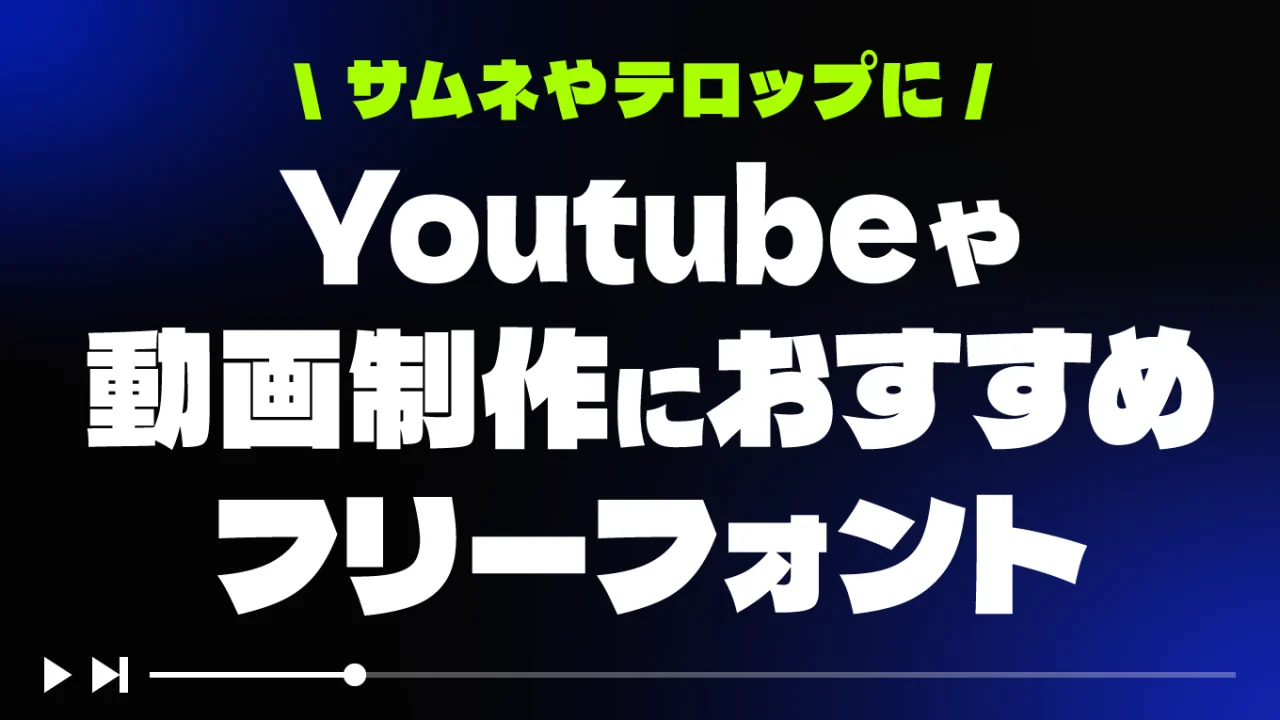
YouTube動画制作の字幕・タイトル・アイキャッチ画像やサムネイル画像におすすめフリーフォントをまとめています。
フォントが変わるだけでガラッと動画の印象が変わるので、自分の動画スタイルにあったフォントを選ぶことがポイントです。
さまざまなYoutube動画のアイキャッチやテロップ使用されているフォントや、Youtuberに人気のあるフォントや動画制作で定番フォントなどのおすすめフリーフォントをご紹介します。
動画制作の字幕やタイトルにフリーフォントのまとめ
本記事で紹介している一部のフォントですが、Youtubeのサムネイルやテロップに使用するとこのようなイメージになるので、フォント探している方は参考にしてみてください。
きんいろサンセリフ
きんいろサンセリフフォントは、人気4コマ漫画のタイトルロゴをモチーフに制作されたフォントです。ユニークなフォルムがポップな印象がでるので、VTuberさんの動画がよく使用されているのを見かけるフォントです。
ABEMA番組「チャンスの時間」番組内のテロップに使用されているので、TV映像でも使われる人気あるフォントです。
キルゴUフォントは、アニメロゴをモチーフとしたフォントです。ゴツゴツしたフォルムが元気でポップな印象なので、サムネイルに取り入れるとインパクトがでること間違いないフォントです。
源暎きわみゴ
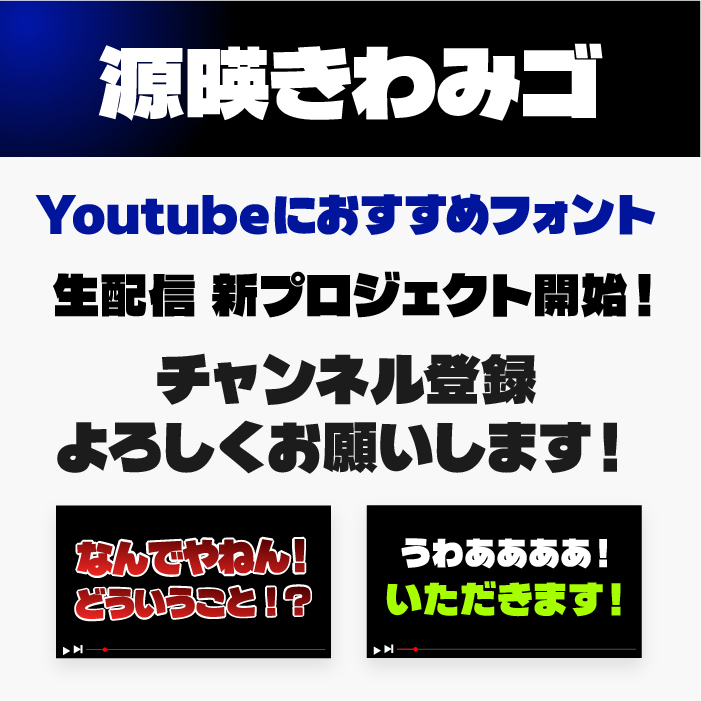
源暎きわみフォントは、超極太フォントで視認性・判読性も高く、強い印象があり、目を引くフォントなので、サムネイルやテロップなどにさまざまな場面で活躍できるフォントです。
不知火
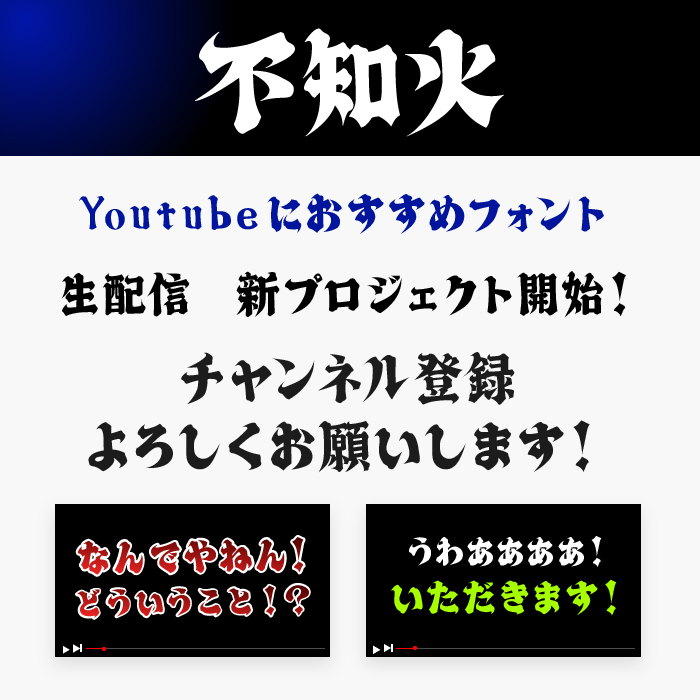
不知火(しらぬい)フォントは、荒々しい筆致が特徴的な力強さを感じる筆文字風フォントです。荒々しさのあるテロップやツッコミを入れたいときにぴったりです。
段太フォント
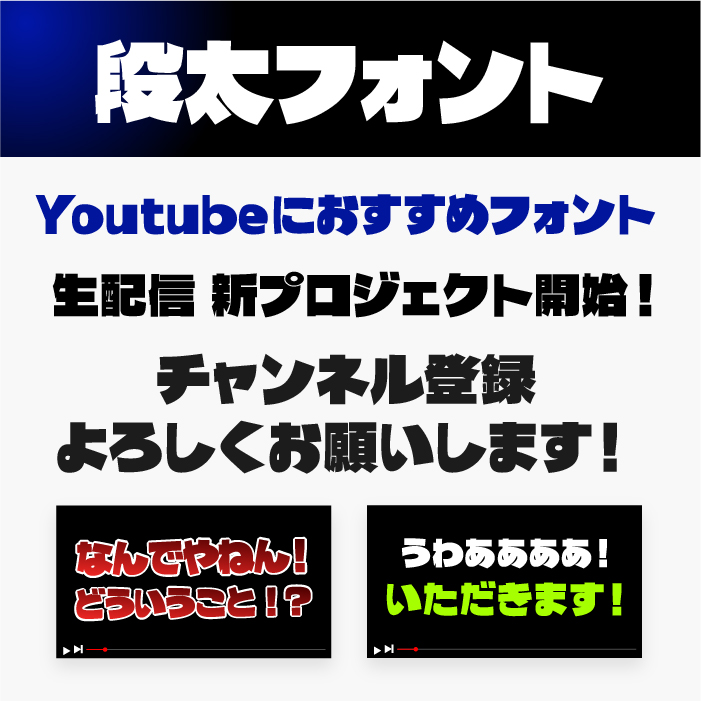
段太フォントは、文字全体を右方へ引っ張ったような重量感がある遊び心があるフォルム、ひと目で目を引くパワフルなデザインです。
雨墨ゴシック
雨墨ゴシックフォントは、輪郭をギザギザなにじみの加工を施しているゴシック体フォントです。
手書きっぽいラフな質感が、Youtube動画にはぴったりなフォントです。
無心(むしん)
無心(むしん)フォントは、ひたすら無心で書き殴って作られた手書きフォントです。何のテーマもコンセプトもない、フォント作者の方が殴り書きした字をそのままフォントにしたというフォントです。
手書きなどの感情を表現するようなテロップや字幕などに使うといい感じになります。
たぬき油性マジック
たぬき油性マジックフォントは、極太の油性マジックで書いたような手書きフォント。
ドン・キホーテや雑貨店にあるようなPOP風デザインの文字やタイトルなどの目立つ文字に取り入れると面白いものが作れそうです。
けいふぉんと
けいふぉんとフォントは、アニメロゴをヒントにして制作された、とっても可愛いフォルムのフォントです。タイトルなどにドーンと使うと印象的なタイトルになります。同人アニメや動画のアイキャッチなどに使うとインパクトやデザイン性が出そうで素敵ですね。
Youtubeのサムネイルやテロップ、どちらにも人気あるフォントです。
ラノベPOP
ラノベPOPフォントは、弾むような楽しい雰囲気の優しいキュートな雰囲気があり、マジックペンで書いたような遊び心があるフォントです。
源暎ぽっぷる
源暎ぽっぷるフォントは、ほどよく太さもあり、コロコロとして楽しそうなフォルムが可愛らしいフォントです。
太さもあるので、小さめのサイズでテロップとしても大活躍できます。大きめのタイトルとして使ってみてもインパクトがあり、柔らかい雰囲気を感じさせてくれるので、エンタメ系・美容系・コスメ系・などなど様々な動画で活躍できるフォントです。
あかずきんポップ
あかずきんポップフォントは、軽やかで弾むような、楽しい雰囲気のキュートなPOP体フォントです。マジックペンで勢いよく書いたような雰囲気と、勢いがある文字の先端に付いている装飾の三角形がアクセントになっているのが特徴です。
文字に動きがあるので、テロップなどに使うとGOODです。
デラゴシックワン(Dela Gothic One)フォントは、超極太フォルムでどっしりしており、縦に少し縮めているようなユニークでインパクトがある平体フォントになっています。
アニメジャンル・VTuber系・ゲーム配信系などのYoutubeなどのサムネイル画像やタイトルロゴなどに向いているフォントです。
でらすこゴシック
でらすこゴシックフォントは、上記のデラゴシックをベースに変形して作られたゴシック体です。デラゴシックの縦横比のバランスが整えられていることで、幅広い場面で使いやすくなりました。
このようにテロップなどインパクトを付けたい場面に取り入れると効果的です。
ふぉんとうは怖い明朝体
ホラー系の表現をしたいなら「ふぉんとうは怖い明朝体」
ホラー系デザインとの相性ととっても良く、ホラー的なタイトルやテロップや効果音などに効果的なフォントです。ホラー系のドッキリものなどでも相性良さそう!
暗黒ゾン字
ホラー系動画や恐怖感を表現をしたタイトルを作るなら「暗黒ゾン字」がオススメ!
太さがあるフォントなので、文字に揺れや血が垂れているような加工がインパクトを表現してくれること間違いなし!恐怖系デザインにはピッタリなフォントになっています。ベタ打ちで使用するだけでも、文字から怖さや動揺が伝わってくるフォントです。
りいクッキー
りいクッキーフォントは、角がカクカクしており、ラインが太めで手書き感あるコロコロとした可愛らしいフォルムが特徴のフォントです。
子供っぽい元気ある楽しい気持ちになれるフォントになっているので、子供向けYoutube番組やチャンネルなどに使うと可愛らしい印象になります。「●●やってみた!」みたいなテンションを上げたいときにもバッチリ良いです。
コーポレート・ロゴ
コーポレート・ロゴフォントは、少し縦長のモダンな雰囲気のゴシック体フォント。角張っておりいい意味で特徴が少なくロゴとして使いやすいフォントかと思います。
汎用的に幅広く使用できる通常フォントです。
ビジネス向けジャンルのYoutube動画でよく使われているのを見かけるので、固くなりすぎず、柔らかくなりすぎ、ちょうどいいバランスのフォントになっています。
コーポレート・ロゴ(ラウンド)
コーポレート・ロゴ(ラウンド)フォントとは、上記で紹介している「コーポレート・ロゴ」に角丸(ラウンド)加工を施したフォントになります。
角丸なのですが、可愛くなりすぎずに固くなりすぎず、ちょうど良く現代的でモダンな雰囲気とシンプルな雰囲気があり、柔らかくて優しい印象が加わっています。
上記で紹介している「コーポレート・ロゴ」よりもう少し崩した印象にしたい、などの場合に使ってみると良いかもしれません。
やさしさゴシック
やさしさゴシックは、「優しい気持ち」で作ったフォント。ゴシック体ですが、全体的に丸みや手書き風のような親しみ感や優しさを感じられるフォントです。
漢字も豊富に揃っており、文字の可読性も非常に優れていますので、動画の字幕やテロップなどに使用されている人気フォントの1つです。
うつくし明朝体
はねやはらいに柔らかさがあることで、レトロな味わい・漢字とかなのバランスなど求められるオールドスタイル明朝体のエッセンスは残しつつ、モダンなフォントです。
和風テイストの日本旅行Vlogや旅行系などのエンタメ動画との相性がとっても良い明朝体フォントになっています。
こころ明朝体
上記で紹介している「うつくし明朝体」より少し長体になっており、スタイリッシュや上品な印象になっているフォントです。
凛としているフォントなので、『お祭り的』『和食的』『庭園的』『寺院』など和風を感じるような動画ジャンルにオススメのフォントです。
毛筆の文字なので和風デザインとの相性はとても良さそうなので、動画のサムネ、キャッチコピーなど、あらゆるシーンに活用できるフォントです。
太さもあるフォントなので、大きくドーンとテロップ的に使っても見ると印象的な動画になるはずです。ドドーンと男らしさを表現するにはピッタリなフォントです。
しょかきうたげ
居酒屋のメニュー風の手書き文字を目指して制作されたフォントです。すべて手書きの字を元に作られているようです。
セリフ言葉のテロップなど感情を入れたいシーンなどにピッタリです。筆っぽい質感ですが、和風な印象もありますが、それ以外のシーンでも活躍できるフォントになっています。
全員集合!ポップ体
全員集合!ポップ体フォントは、手書き文字フォントとしてもかわいい仕上がりですが、80年代のテレビ番組でしようされていた手書き文字をイメージしているとのこと。
どこか懐かしいレトロな趣がある手書きになっているので、レトロな印象の動画を作りたい場合に取り入れてみると面白いフォントです。少しエモさも感じるので、エモさを表現したい動画などに取り入れてみても素敵なフォントかと思います。
チカラヨワク
フニャフニャした弱々しい様子が表現されているフォントです。
上記画像サンプルのように、弱々しい表現やセリフなどのテロップや字幕などでよく使用されているフォントの1つです。文字から申し訳無さが伝わってくる素敵なフォントです。
チカラヅヨク
荒々しく殴り書きをしたような躍動感ある文字が表現されている手書き系フォントです。
上記のように、ツッコミ系テロップや荒々しい表現やセリフなどのテロップや字幕などでよく使用されているフォントの1つです。文字から躍動感が伝わってくる素敵なフォントです。